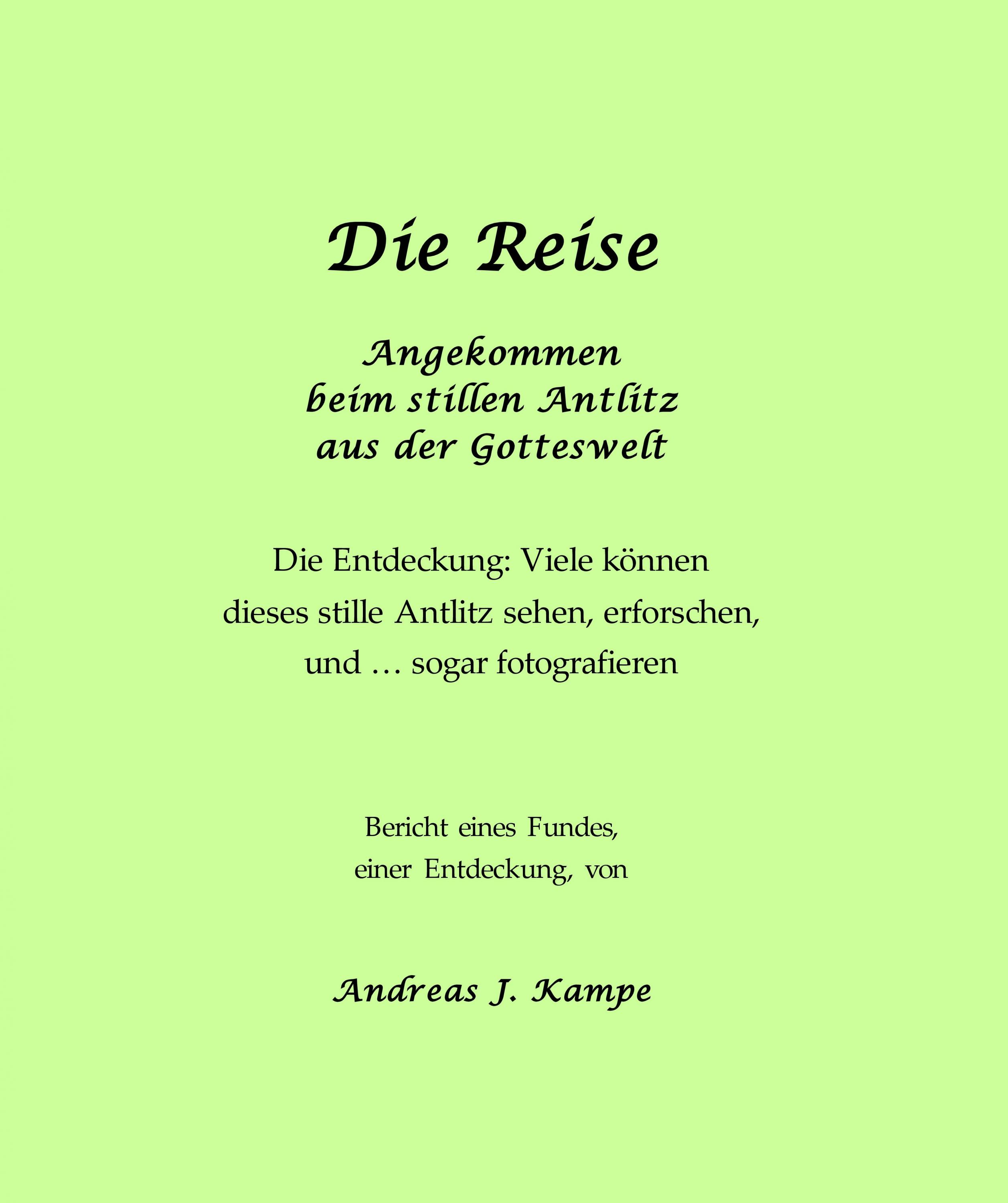
Schrift für Papierbuch bei CreateSpace, font extra bezahlen?
Hallo, Freunde der Schriften,
Bin dabei, ein paperback für createspace zu entwickeln. Jetzt vernahm ich bei fb und der sp gruppe self publisher, dass man für sylvaen eine lizenz erwerben müsste.
Auf dem Template dieses Buchformates (und auf allen templates von CS) ist garamond schon drauf, die ich etwas kringelig finde, viell. wäre sie in 12 pt stärker lesbar. Hat amazon createspace diese garamond vielleicht schon bezahlt?
Doch eigentlich wollte ich nun in die Schrift kein Geld investieren. Habe zwar ein wahrhaftes Superthema, doch wollte ich erst mal einen Versuchsballon starten; meist sieht es ja nicht so gut aus mit der Resonanz. Mir geht es nicht ums Geld machen, mal so gesagt.
Es wurde mal vollkorn empfohlen, doch mein win 10 nimmt das nicht an.
Die sylvaen in 11pt finde ich charakterstark und gut lesbar. Oder welche Möglichkeiten sonst, bitte? Möglichst ehrlich zum Anfang kostenfrei -
Exakt, Norbert, genau diese. Mein Script führe ich nun in dieser aus. Gefällt mir. Doch durch andere Projektkosten ist es derzeit knapp.
Also lässt sich andere finden, die frei von Kosten ist?
Der Lizenz nach wie open source?
Nun 49 E. könnte ich noch bezahlen, da das erst in 2, 3 Monaten rauskommt, wie ich hoffe. Doch wo und wie, und ob das für ein paperback ist, oder mehrere, man wird aus der Seite auch nicht gerade schlau. Wenn sie Geldgeschäfte machen - ist es microsoft, der der Entwickler und Schriftgestalter? - könnten sie zumindest einen schlau machen durch das Deutsche.
Was die Garamond anbelangt, wenn die für ihre Arbeitsplätze Lizenzen dieser Schrift erworben haben, gelten diese auch nur, für das was dort auch gesetzt wird. Wenn du also deren Premiumservice nutzt, da nur Word-Dateien mit irgend einer Systemschrift einlieferst und die bauen dir da einen typografisch korrekten Satz in Garamond, dann benötigst du keine Lizenz.
Und wenn du das aber selber gestalten und setzen möchtest, und dazu eben auch Garamond nutzen willst, dann bräuchtest du - auch wenn die in den Templates schon verwendet wurde, für DEINEN Arbeitsplatz selbst eine Lizenz dieser Schrift.
Und wenn du dann eine Desktop-Lizenz einer Schrift erworben hast, gilt die nicht nur für ein bestimmtes Projekt, also dein Buch, sondern für alles, was du von da an mit dieser Schrift gestalten möchtest. Weitere Bücher, Werbeflyer, Plakate für die Buchmesse und wer weiß was - außer eben als Webfont auf der Website, das kostet zuzmeist extra. Sonst aber ist die Schrift dann ein einmal bezahltes Werkzeug, das du immer wieder nutzen darfst.
Diese Templates sind halt alle völlig in Garamond geschrieben, die mir nicht so  zusagt. Kringel, für Frauen und Mädchenromane ...  Eine Massenformatierung, alles in Garamond. Man kann ja die Schrift wechseln.
Früher war ich mal, Catfonts, auf einer Schule für Grafik, Druck und Werbung, was nachher zum "Kommunik.Gestalter" wurde, mich jedoch ebenso anwiderte nach 2, 5 Jahren. Also ein wenig habe ich Ahnung. Da diese Schule wiederum aus einer Schule für Buch und Druck hervorging, in Berlin.
Diese Ahnung ließe mich die Sylfaen bevorzugen. Wie ist das denn, wie und wo wird dort bezahlt? Habt Ihr da Erfahrung?
Oder gäbe es eine Möglichkeit einer ganz kostenlosen passablen Schrift, ich hörte von der Schrift Vollkorn, kann sie jedoch bei Win10 nicht übernehmen (Fehlmeldung).
Das ist mir also auf jeden Fall unklar,
da alles so schön in englisch formuliert ist,
Oder gäbe es auch freie kostenlose Schriften? Wo man dann nur den Designer zitiert?
Jetzt erst einmal die Frage: Was genau gab es bei der Vollkorn für Fehlermeldungen? Ich hab die nämlich problemlos in Win10 installiert.
Für einen anderen Nutzer hier hatte ich die Doppelkorn ein wenig ergänzt (die Lizenz lässt das bei dann Namensänderung ja zu) und habe sie dann "Doppelkorn" genannt. Probier die mal, ist ja im Grunde die gleiche Schrift:  Doppelkorn.zip
Sonst solltest Du mal die Source-Familie bei Google Fonts in Augenschein nehmen: https://fonts.google.com/specimen/Source+Serif+Pro